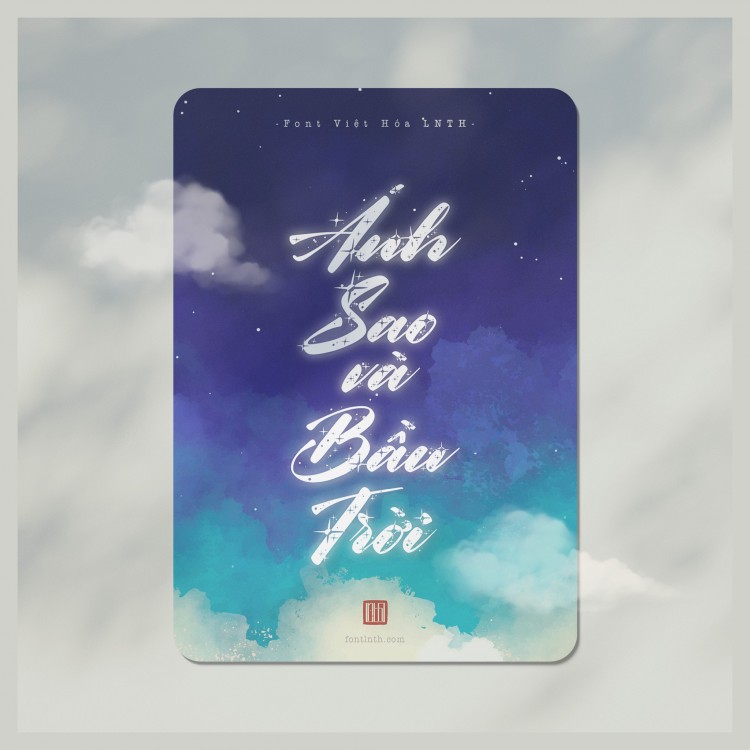
Font việt hóa LNTH Christmas in Brighton – Nét đẹp mùa lễ hội lung linh
Trong thế giới thiết kế đồ họa, việc lựa chọn một bộ Font Chữ phù hợp chính là chìa khóa để truyền tải linh hồn của tác phẩm. Đặc biệt, bộ Font việt hóa LNTH Christmas in Brighton đang trở thành tâm điểm chú ý nhờ phong cách viết tay thanh thoát và đầy cảm xúc. Đây là lựa chọn hoàn hảo cho những ai muốn tạo nên các sản phẩm sáng tạo mang đậm chất cổ điển nhưng vẫn giữ được vẻ hiện đại, gần gũi trong môi trường học đường và cuộc sống hàng ngày.
Khám phá vẻ độc đáo của Font việt hóa LNTH Christmas in Brighton
Bộ font này được lấy cảm hứng từ không khí ấm áp của mùa Giáng sinh tại thành phố Brighton xinh đẹp. Những đường nét mềm mại, uốn lượn tự nhiên giúp văn bản trở nên sống động hơn bao giờ hết. Font việt hóa LNTH Christmas in Brighton đã được tinh chỉnh kỹ lưỡng về bảng mã Unicode, đảm bảo người dùng có thể gõ tiếng Việt mượt mà trên các phần mềm phổ biến như Photoshop, Canva hay Microsoft Word mà không lo lỗi font.
Ứng dụng trong giáo dục và thiết kế
Nhờ tính thẩm mỹ cao, font chữ này thường được các giáo viên và học sinh ưu tiên sử dụng để làm thiệp chúc mừng, thiết kế bìa báo tường hoặc trang trí các slide thuyết trình. Sự kết hợp giữa nét chữ nghệ thuật và khả năng hiển thị rõ ràng giúp các thông điệp được truyền tải một cách chân thực và giàu cảm xúc nhất. Ngoài ra, các nhà thiết kế tự do cũng dùng nó để xây dựng bộ nhận diện thương hiệu mang phong cách nhẹ nhàng.